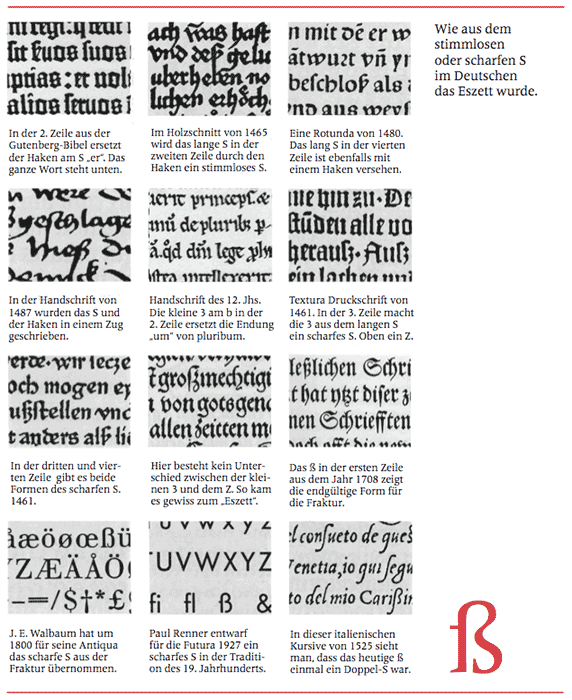
Und wieder das lange s.
Aus den entsprechenden Fehlern des 20. Jahrhunderts hat man doch gelernt.
Max hat mir die Seite seines Buches zum hier veröffentlichen geschickt.
(Anmerkung von mir: Dass die Walbaum-Antiqua um 1800 ein Eszett gehabt hätte, wäre mir neu. Ich kenne die gezeigte Form erst aus den Brockhaus-Proben aus dem 20. Jahrhundert, nachdem ja das Sulzbacher Eszett eingeführt und das Antiqua-ß etabliert war.)
Ich habe mir mal die Seite von Max angeschaut. Ich denke er geht zeitgeschichtlich bei seiner Recherche nicht weit genug zurück, nämlich in die Zeit der Handschrifen, um die Ursprünge des Eszett beurteilen zu können. Alle gedruckten Formen des Eszett imitieren handschriftliche Zeichen, die es zu ergründen gilt. Außerdem wird bei ihm das s mit Haken – um das es hier ja geht – in den Topf mit dem Eszett geworfen, was mir etwas Kopfschmerzen bereitet.
Offtopic zum Eszett: ich gehe von der Theorie aus, daß das Eszett seine Ursprünge in einer tironischen Note hat, die Doppel-s abkürzte. Im Druck imitierte man sie, um Papier-Platz zu sparen und/oder einen schönen Zierat zu haben, so wie man auch “&” für et druckte. Später dann wurde das Zeichen für den Laut scharfes S genutzt bzw. umdefiniert. Genauso wie der Zierat “j” später zum Zeichen für den j-Laut umdefiniert wurde.